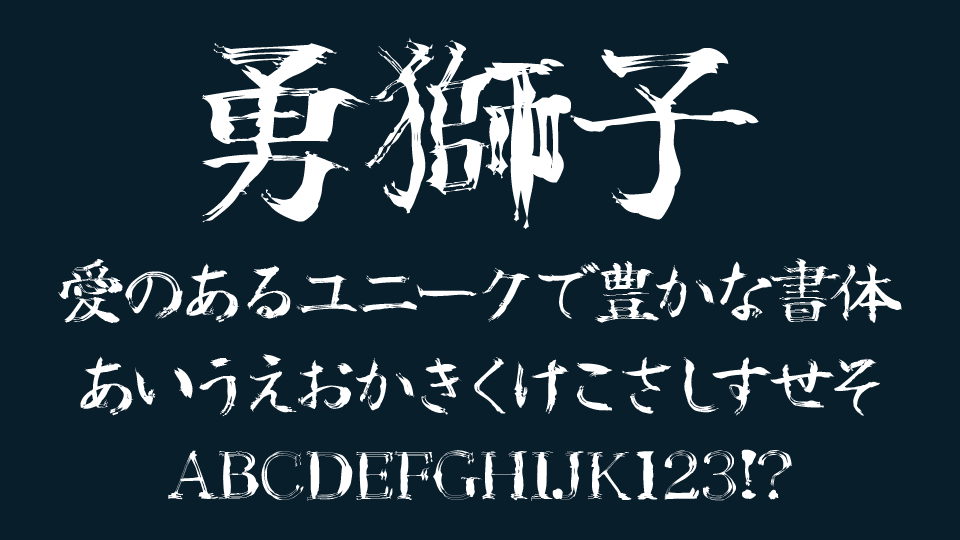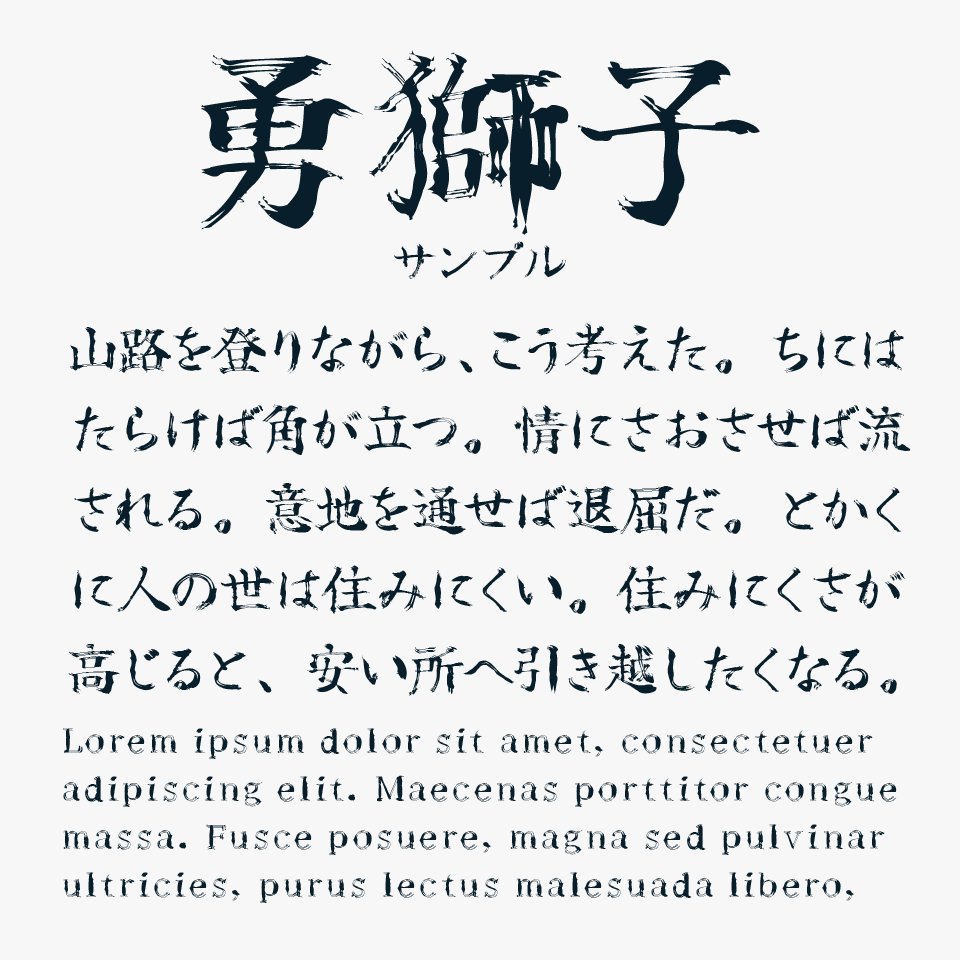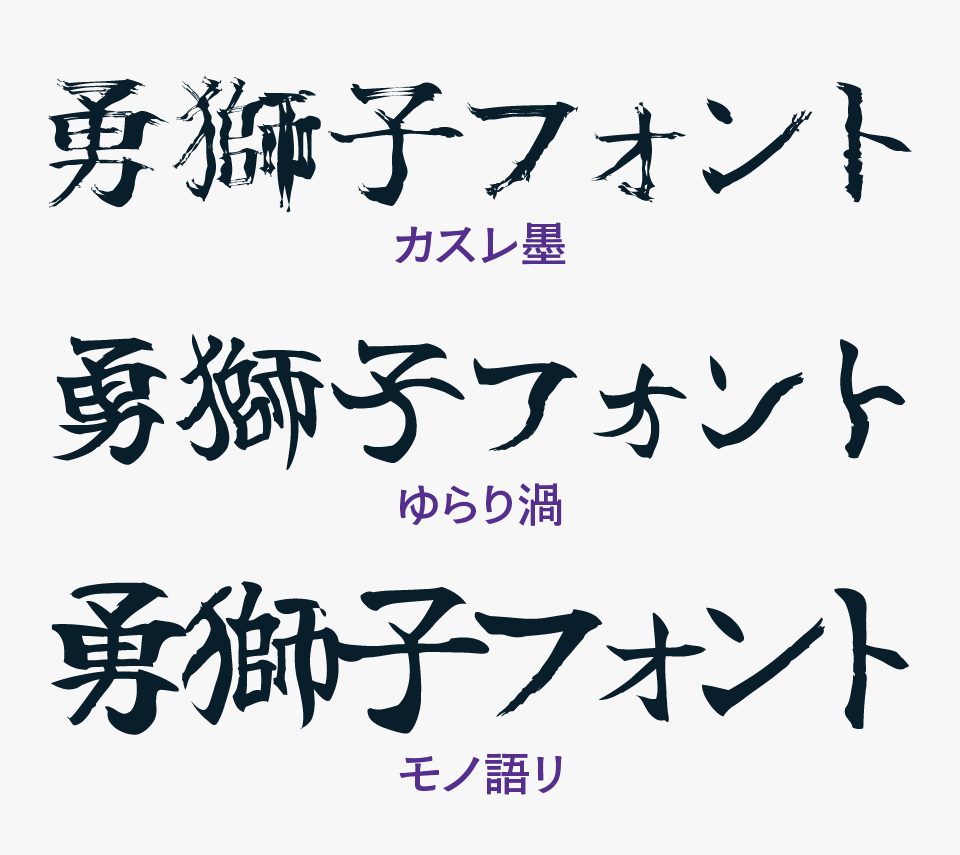
勇獅子
勇獅子フォントは、「佑字【肅】」フォントをベースとして、筆の勢いと荒々しいタッチに調整された迫力満点の筆文字フォントです。
太い筆で一気に書き上げたかのような強いストロークと、文字の端に残る鋭いかすれが、力強さと緊張感が表現されているかっこいい筆文字となっています。獅子を連想させるような堂々とした風格を感じさせるデザインです。
8種のバリエーションと多く揃っており、以下のサンプルは「カスレ墨」「ゆらり渦」「モノ語リ」と、バリエーションによってまた違う表現をもつところも面白いフォントです。